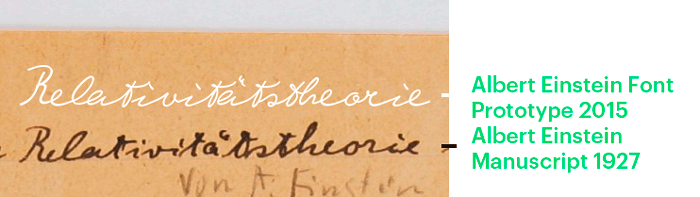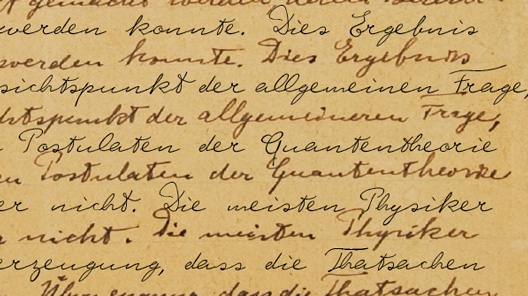
Немецкий дизайнер создает шрифт Эйнштейна
На Kickstarter запущен сбор средств на проект, в рамках которого немецкий дизайнер Гаральд Гейслер разрабатывает шрифт на основе почерка Альберта Эйнштейна. Вместе с ним над проектом работает физик из Гарварда Элизабет Уотерхаус.
Перед тем, как приступить к реализации проекта, дизайнер изучил сотни документов, записей и сочинений знаменитого физика. Для того, чтобы пользователи в дальнейшем смогли "писать как гений", ученые создают цифровые копии каждой рукописной буквы из архивных записей Эйнштейна.
Сам же дизайнер Гейслер не намерен останавливаться только на одном лишь шрифте Эйнштейна: в дальнейшем он планирует создавать и другие шрифты, основанные на почерке различных известных людей. Первым же проектом немецкого дизайнера в 2013 году стал шрифт, имитирующий почерк Зигмунда Фрейда.